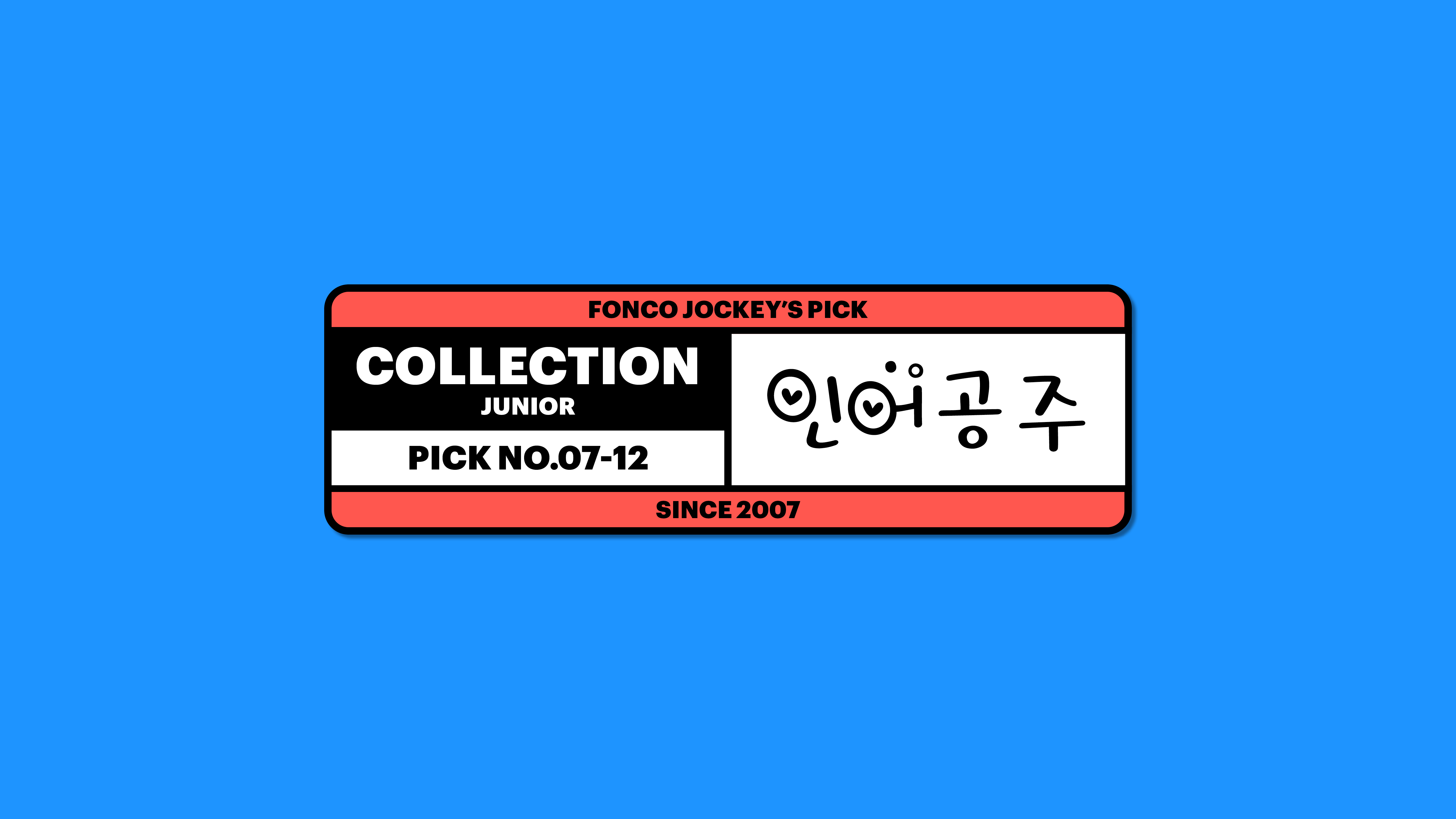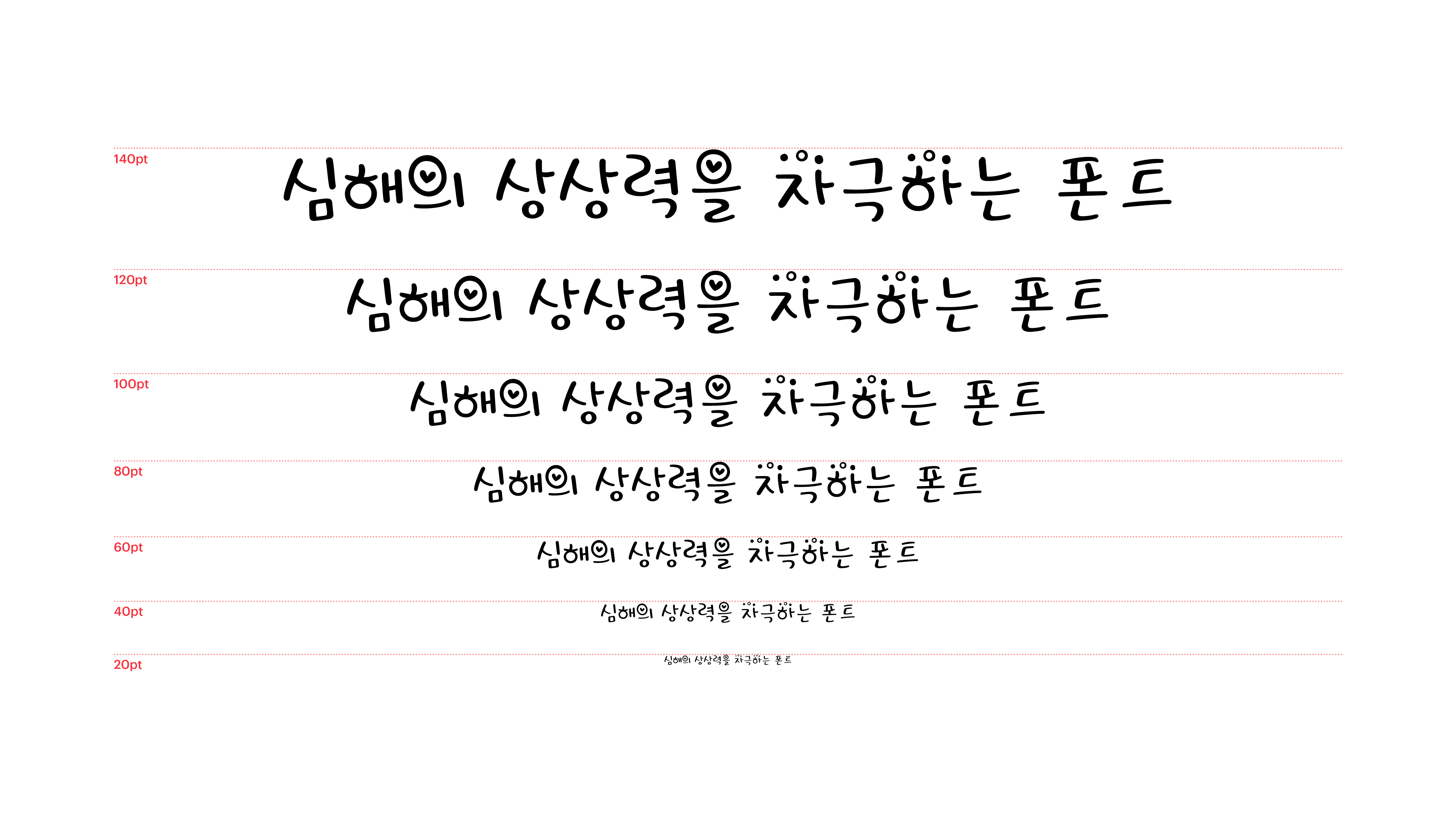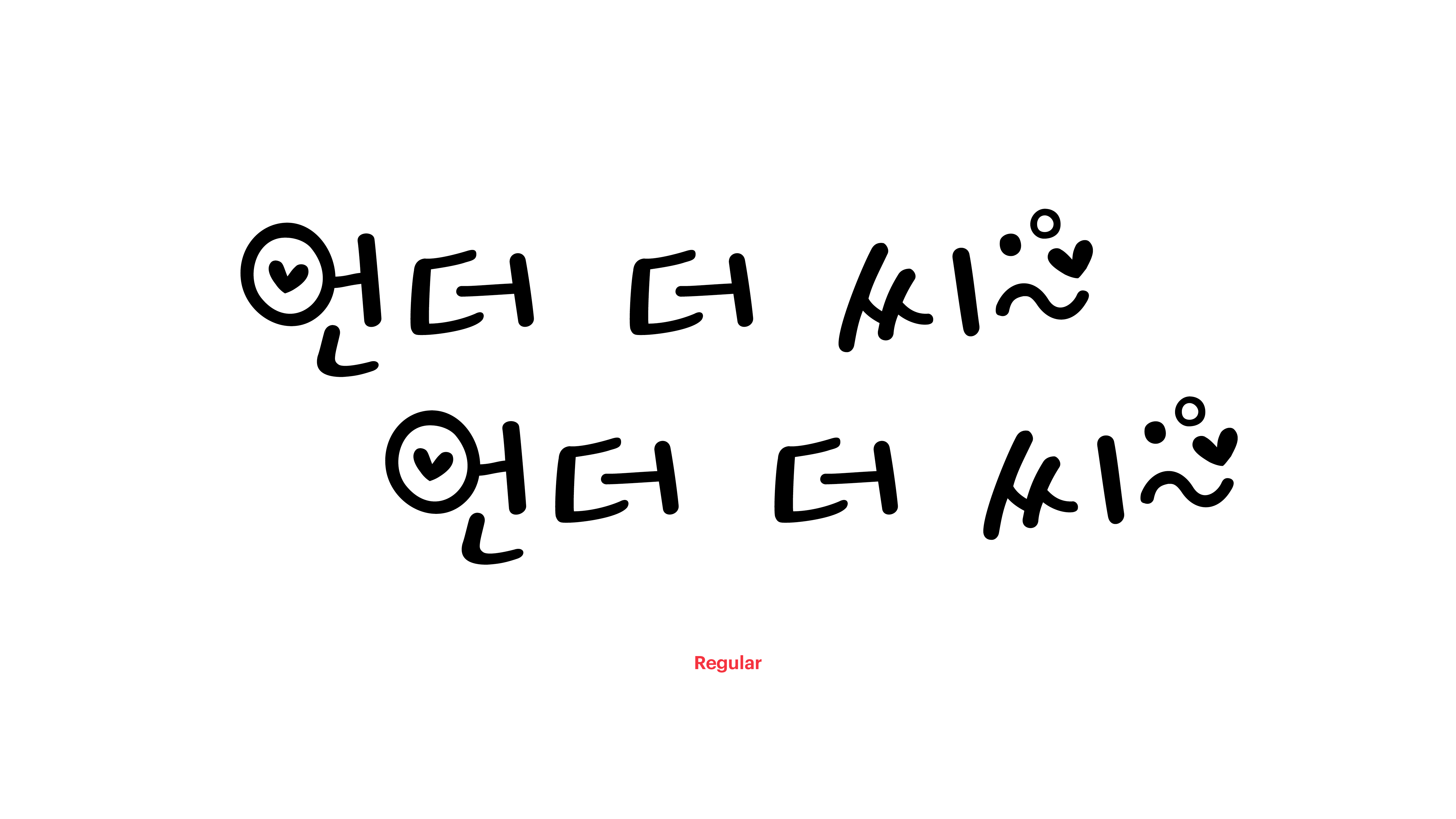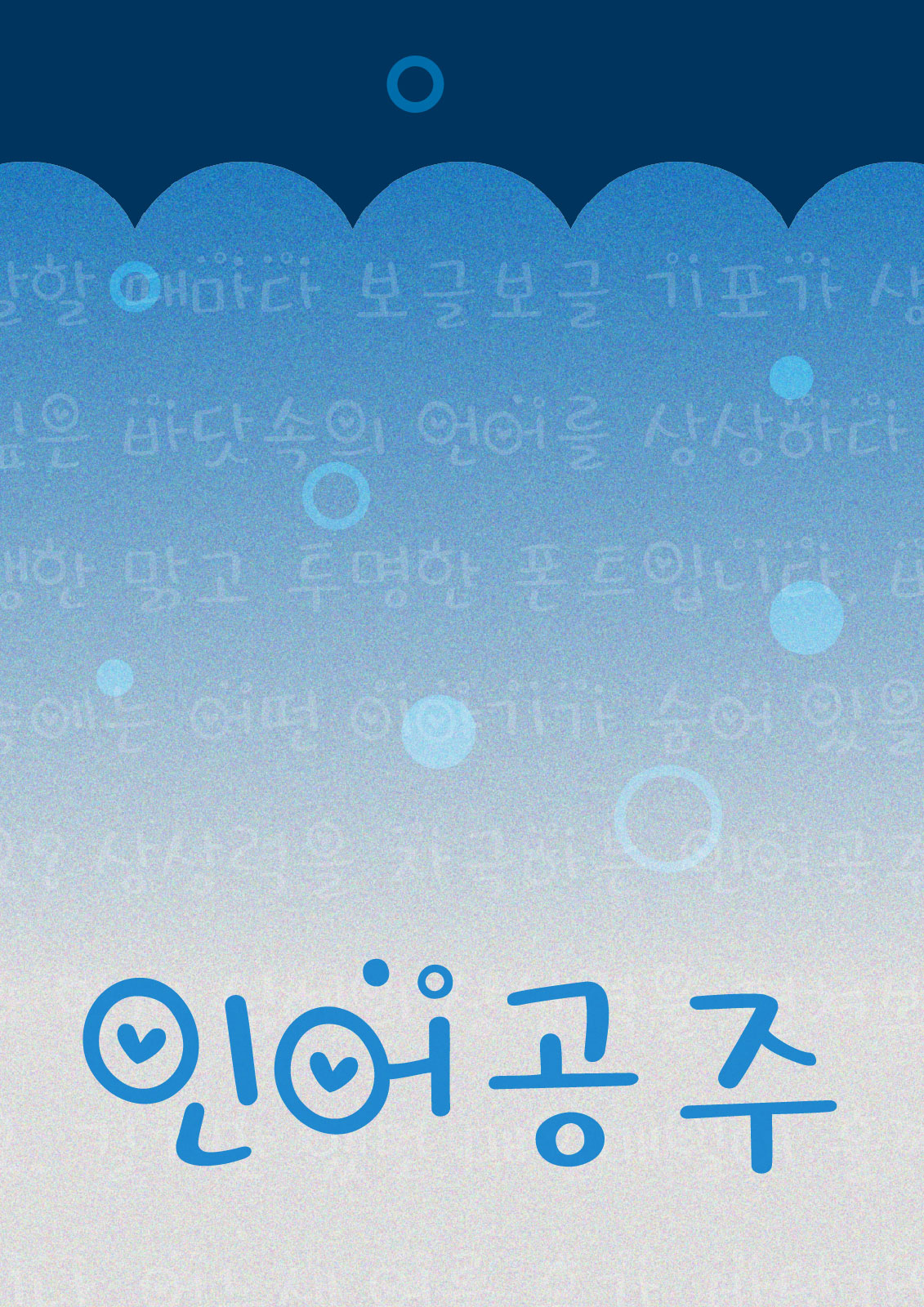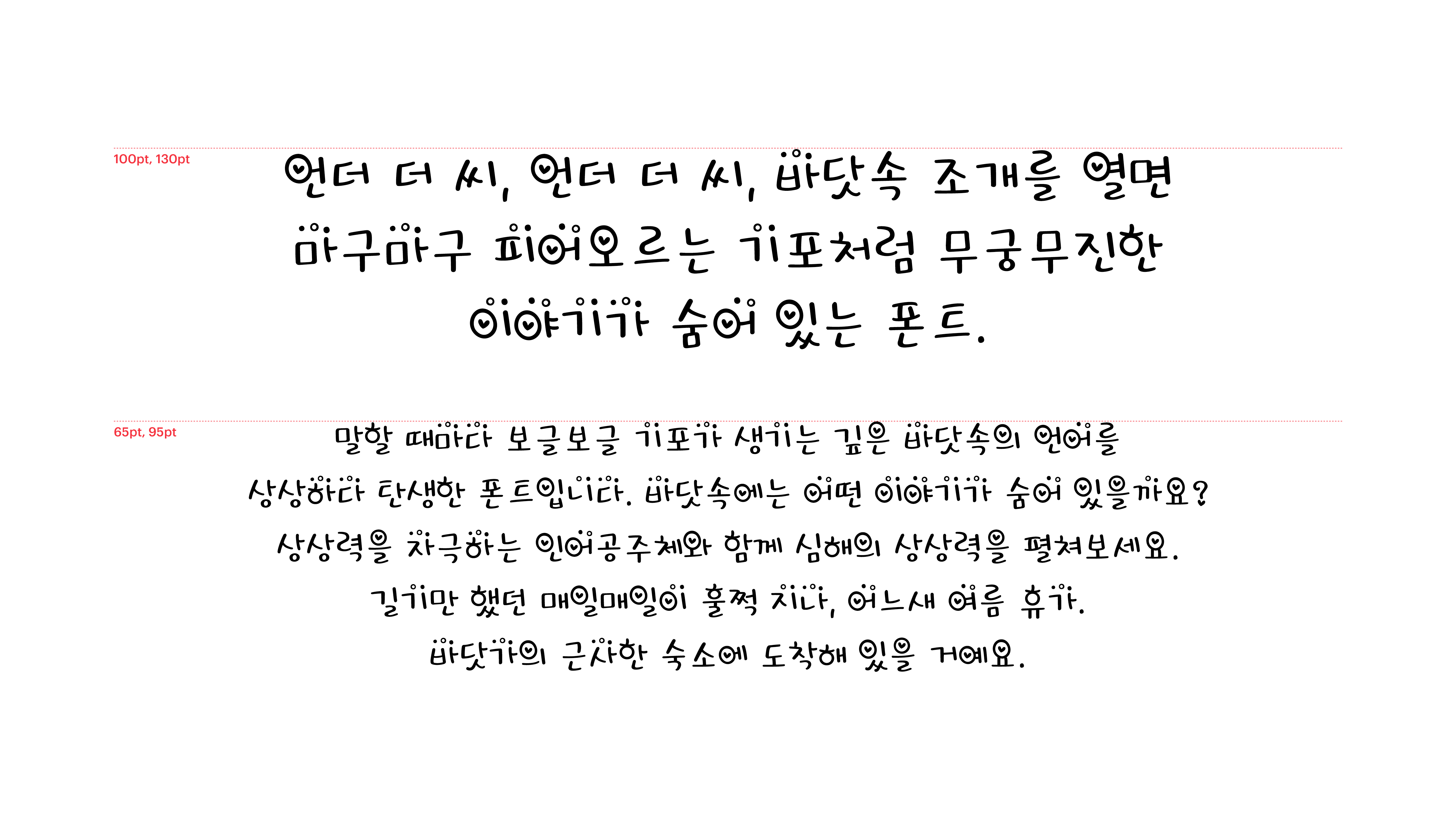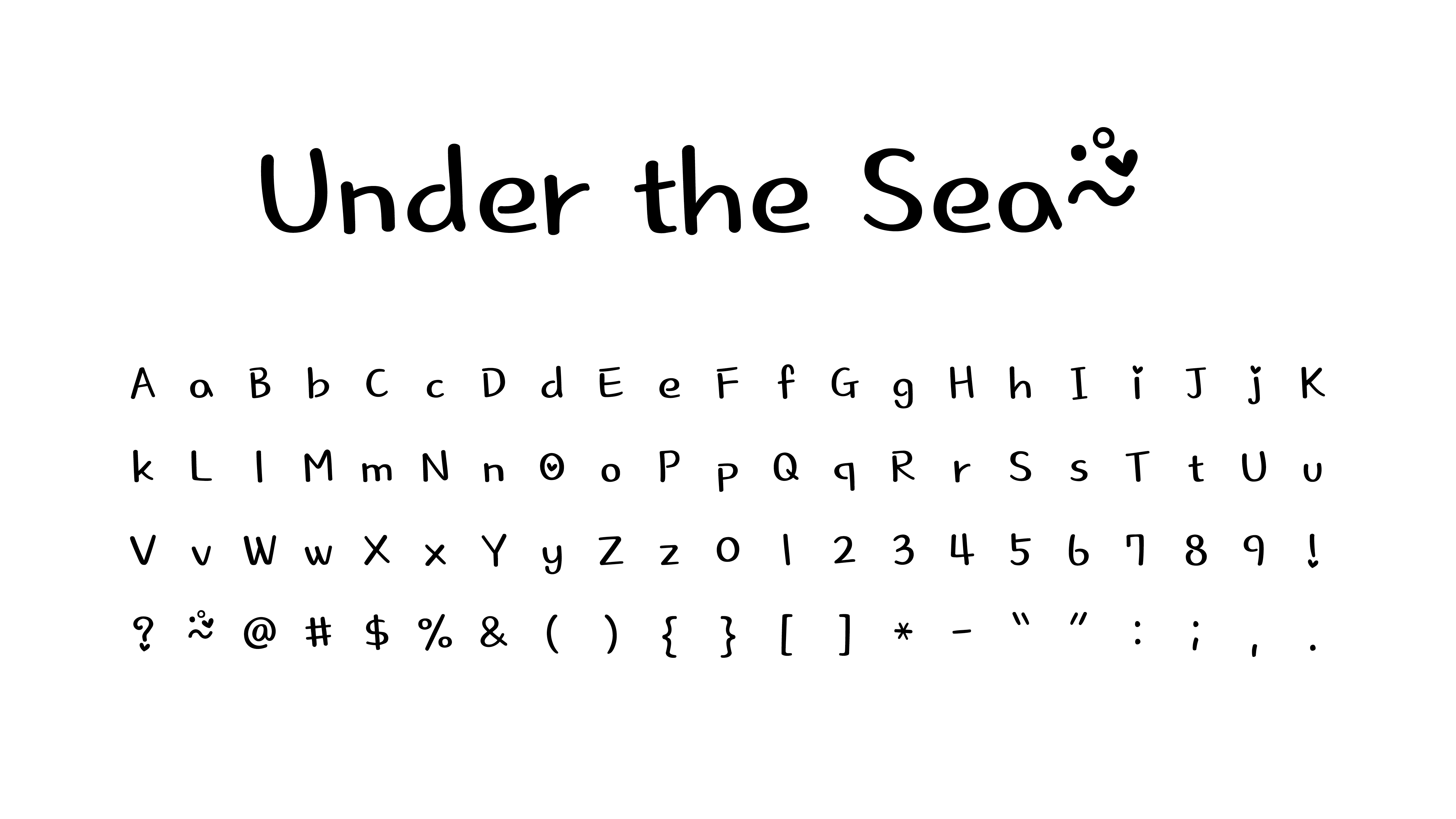
인어공주
Yoon 인어공주
말할 때마다 보글보글 기포가 생기는 깊은 바닷속의 언어를 상상하다 탄생한 맑고 투명한 폰트입니다. 바닷속에는 어떤 이야기가 숨어 있을까요? 상상력을 자극하는 인어공주체와 함께 심해의 상상력을 펼쳐보세요. 길기만 했던 매일매일이 훌쩍 지나, 어느새 여름 휴가. 바닷가의 근사한 숙소에 도착해 있을 거예요.